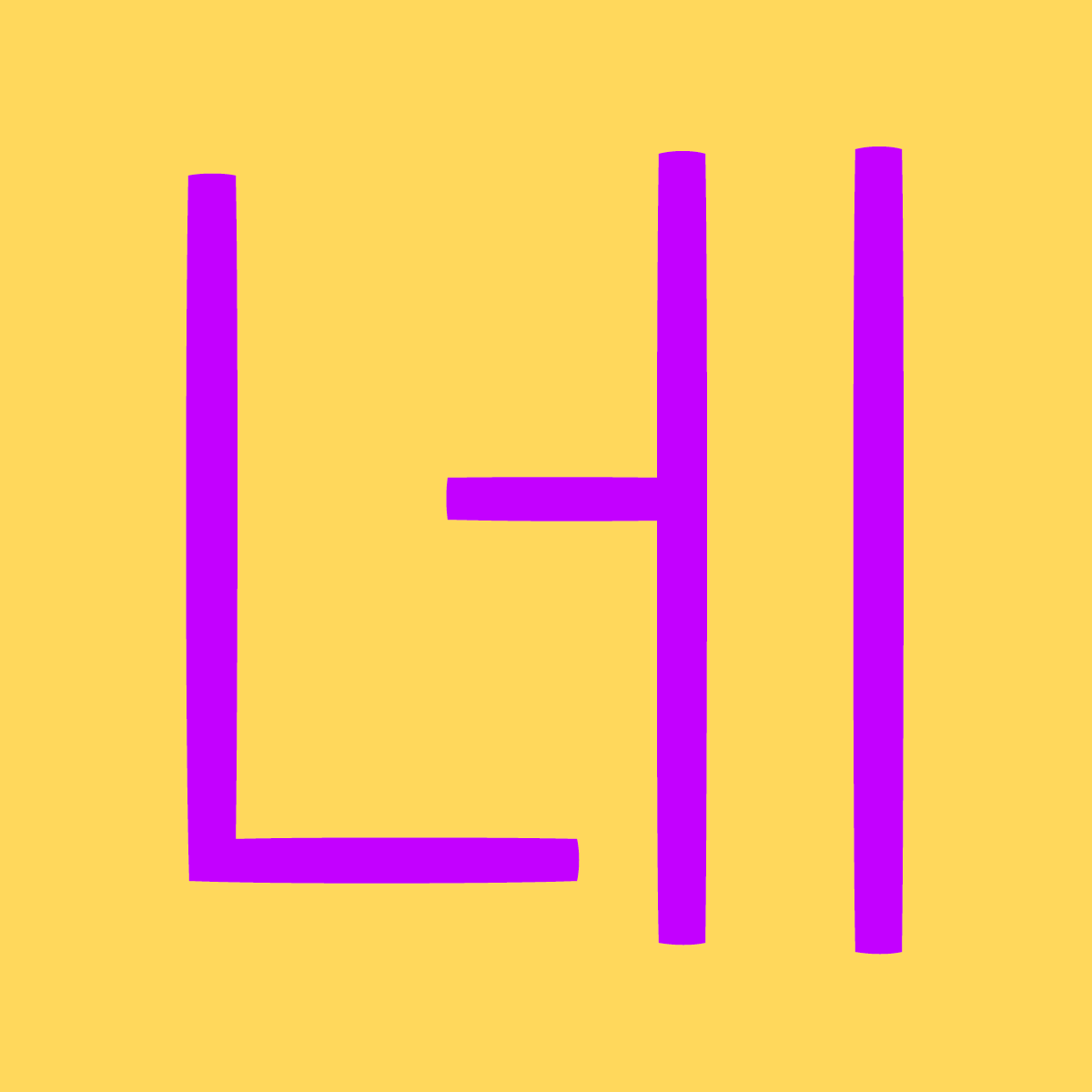
Sandoll 네모니2
산돌 네모니2는 2018년 8월 출시되었던 기존 네모니의 웨이트를 확장한 네모니의 두 번째 버전입니다.
Bold 웨이트만 있었던 전작에 비해 Thin, Light,Regular, Heavy 등 4개의 웨이트가 더해졌기 때문에 좀 더 다양한 작업에 활용할 수 있게 되었으며, 한글 430자를 추가 제작해 '뀰, 똠'과 같은 글자들도 타이핑이 가능해졌습니다.
본문부터 헤드라인까지 전방위로 활용가능하며 트렌디하고 감각적인 디자인 작업을 할 때 사용하기 좋습니다.
2022년, 보다 다양한 사용자들이 다양한 곳에 네모니를 사용하기를 원하는 마음을 담아, 네모니2는 지원하는 언어를 늘렸습니다.
한글은 11,172자로 확장하여 기존에 표기가 되지 않던 한글 모두 사용할 수 있습니다. 또한 라틴 확장을 추가 제작하여 독일어와 프랑스어를 비롯한 대부분의 유럽권 언어, 그리고 베트남어까지 지원합니다. 게다가 키릴 베이직 문자가 추가되어 네모니를 사용하여 러시아어도 표기할 수 있게 되었습니다.
세계를 향해 뻗어나가는 네모니2, 앞으로 또 어떤 언어를 지원하게 될지 기대해 주세요!